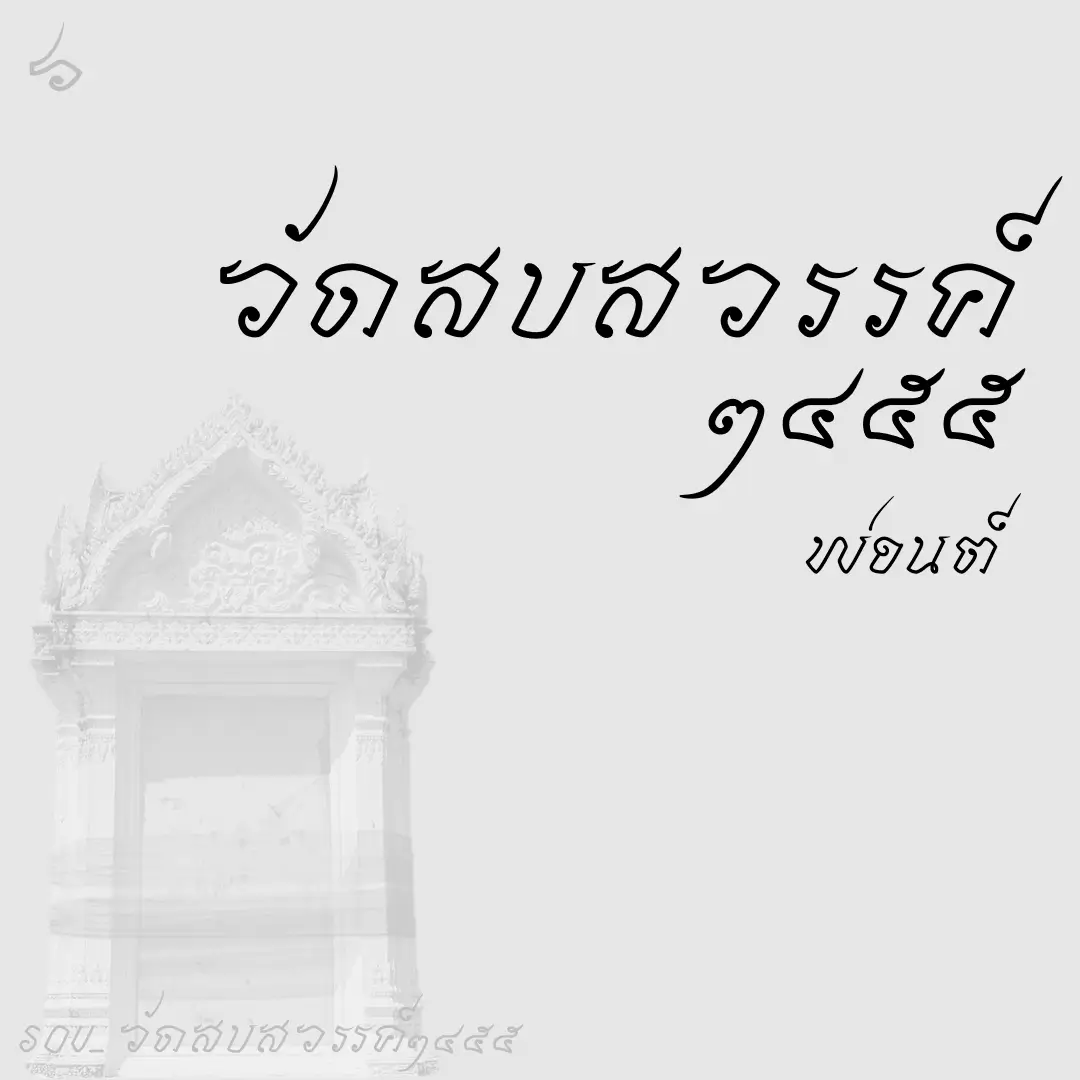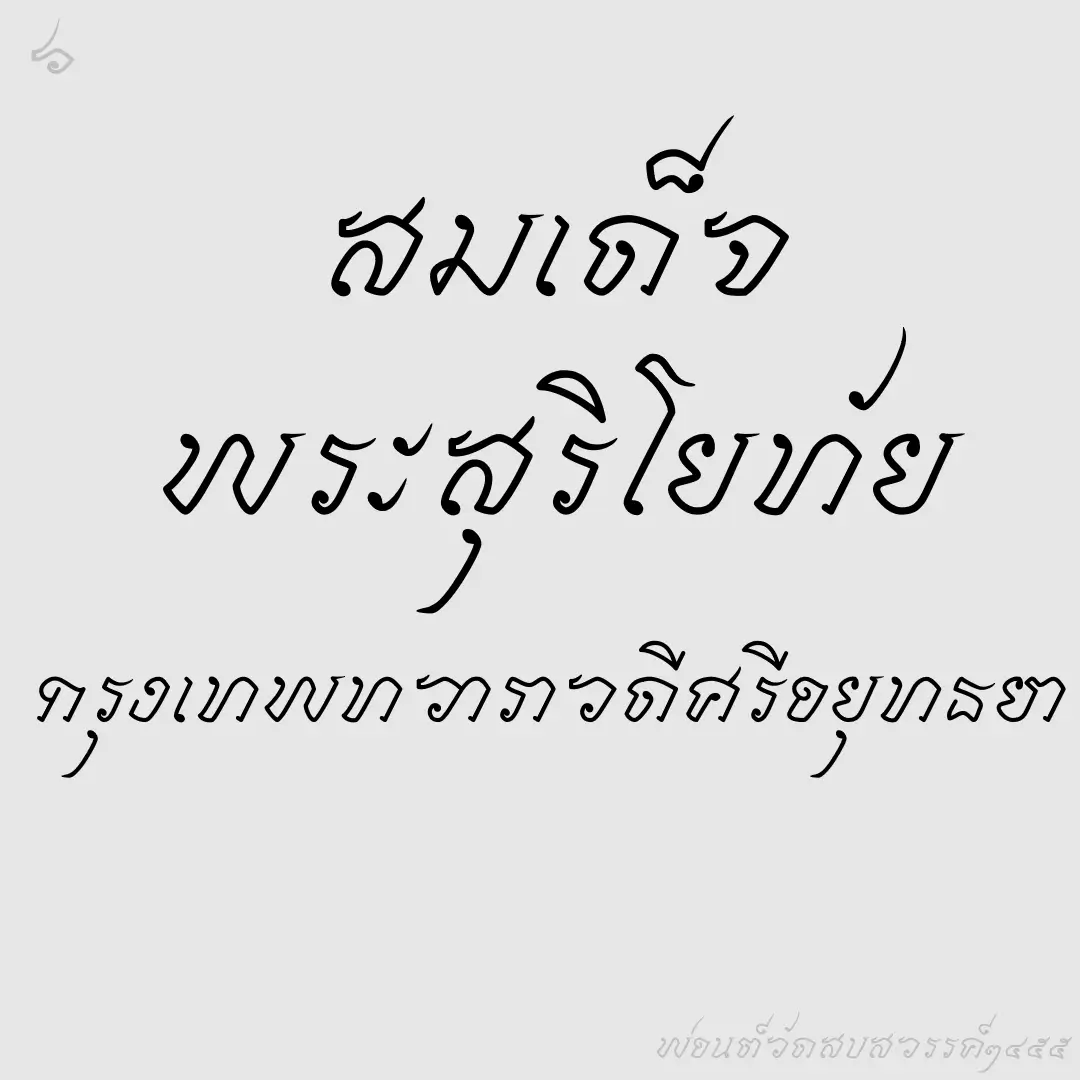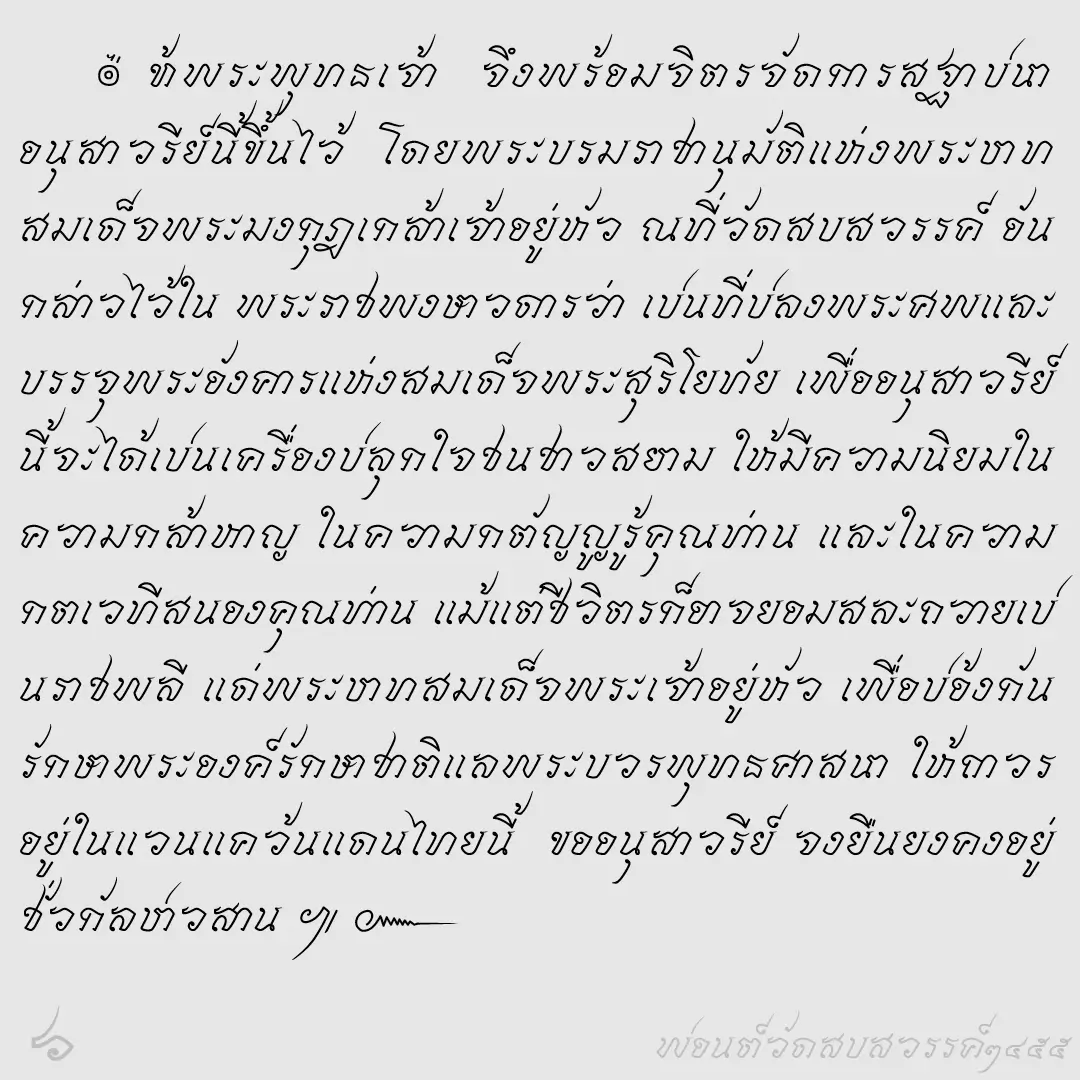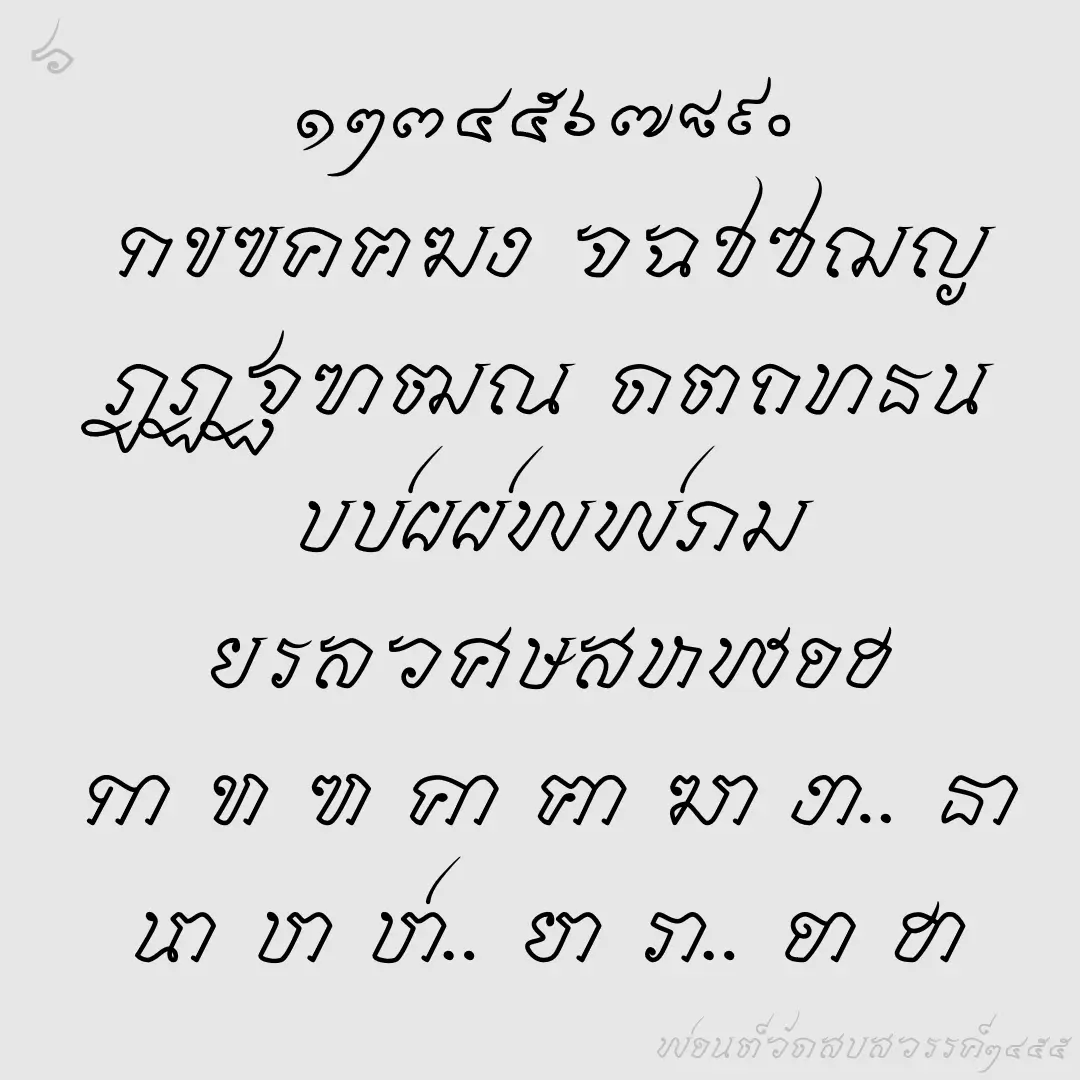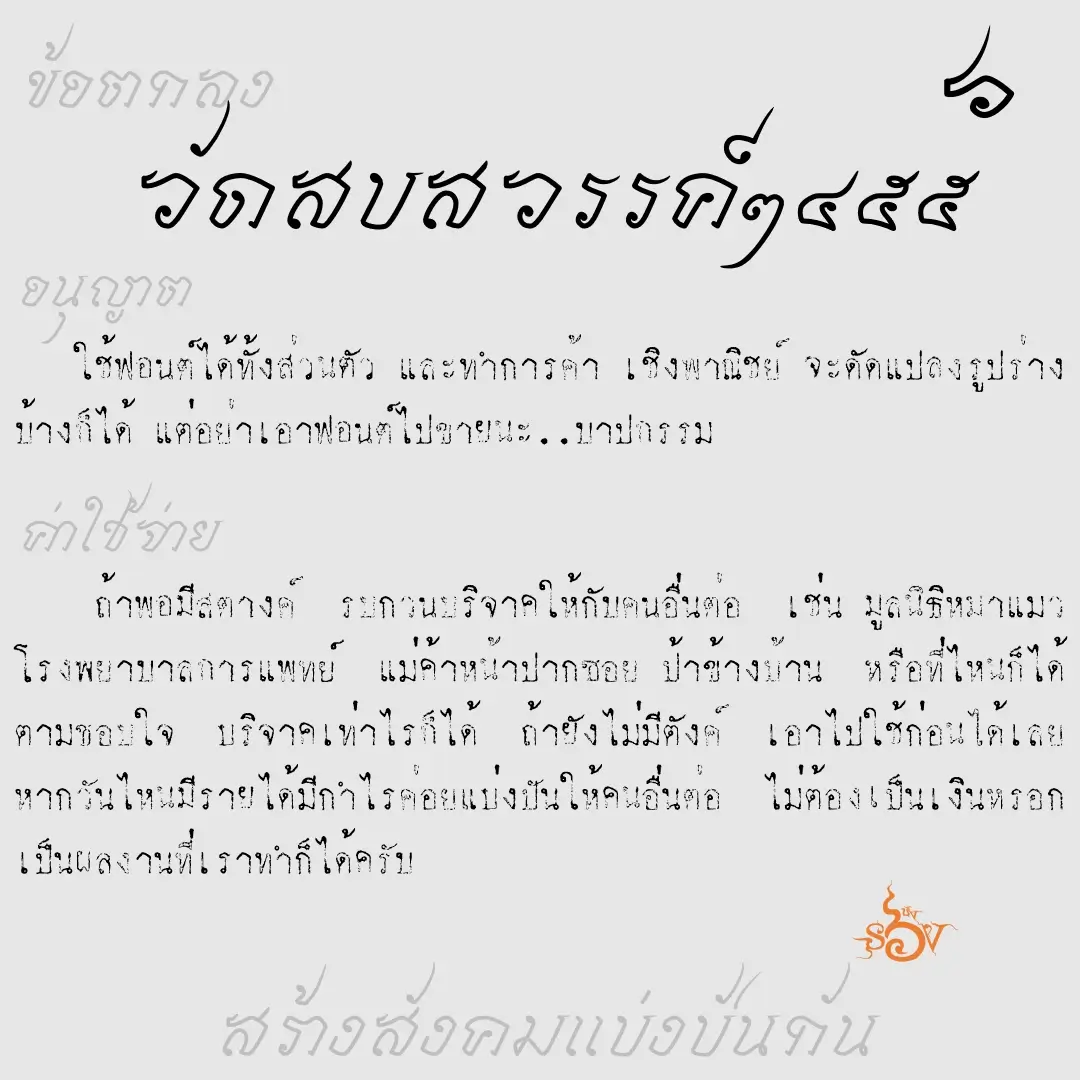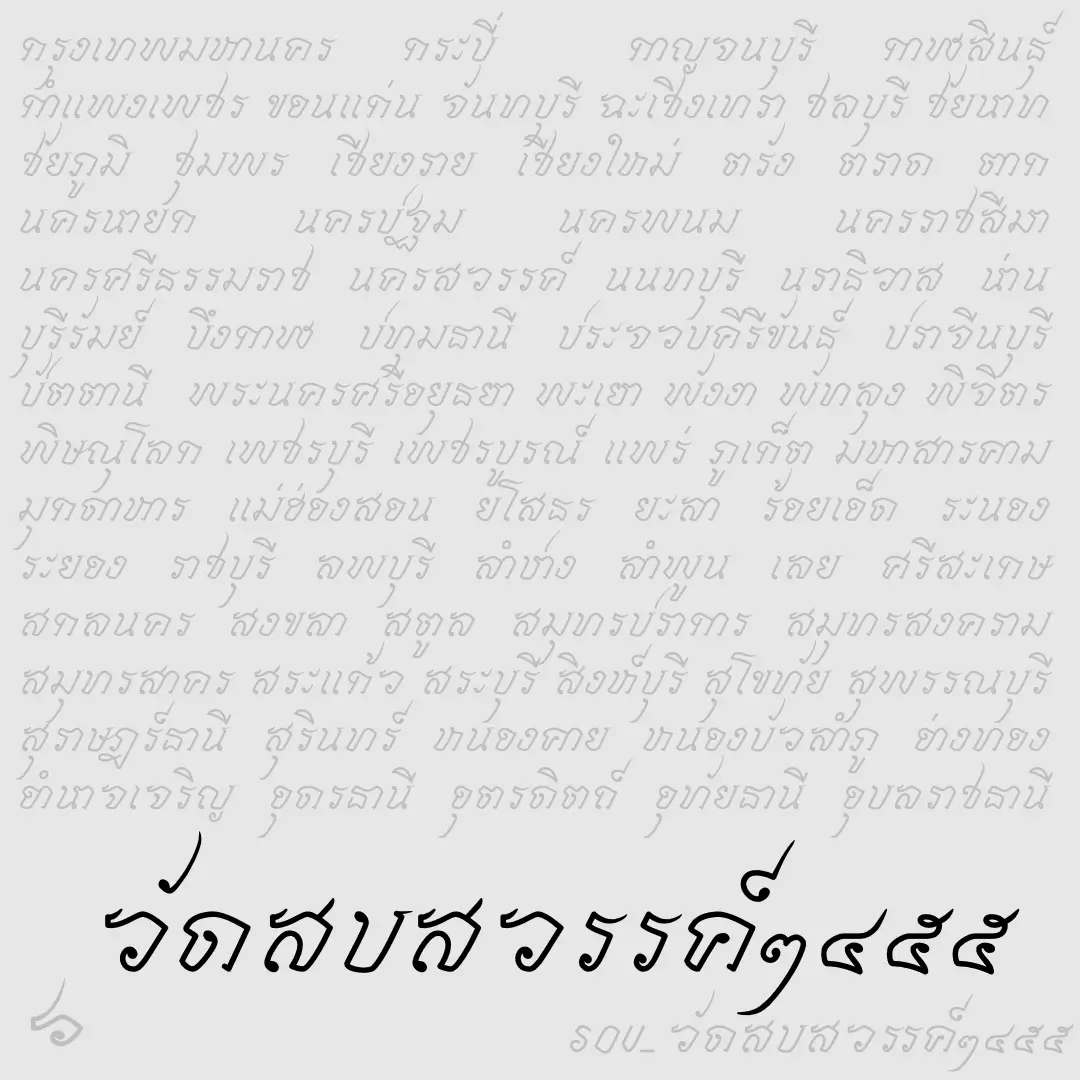
ฟอนต์วัดสบสวรรค์ ๒๔๕๕ – ต้นแบบฟอนต์จาก จารึกอนุสาวรีย์วัดสบสวรรค์ อยู่ในเกาะเมืองอยุธยา ใกล้ๆ กับเจดีย์ศรีสุริโยทัย สร้างขึ้นใน พ.ศ.๒๔๕๕ เพื่อยกย่องสมเด็จพระสุริโยทัย
เบื้องหลังการออกแบบ : ฟอนต์ วัดสบสวรรค์
วัดสบสวรรค์ ๒๔๕๕ (SOV_watsopsawAn2455)